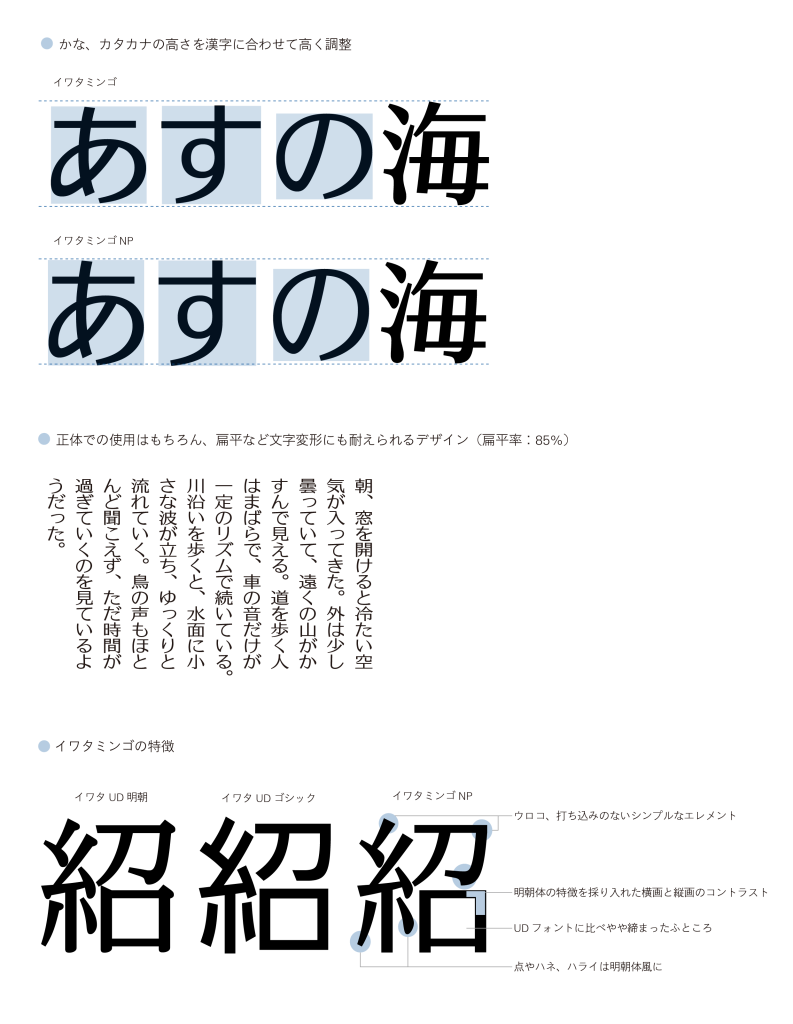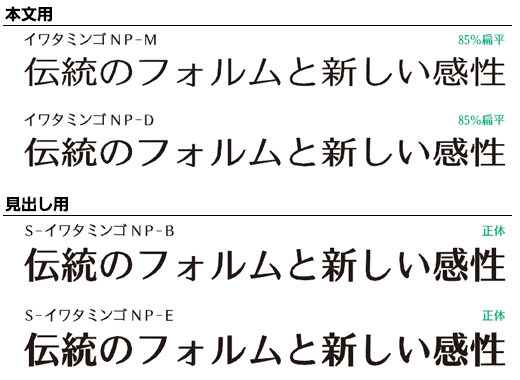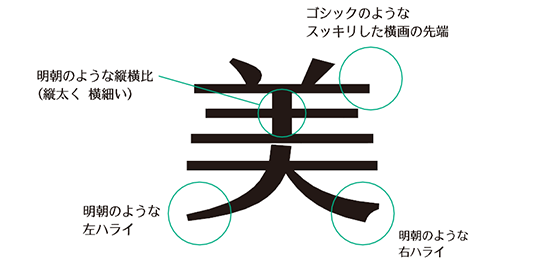
すっきりして優しい表情を持つ「イワタミンゴ」を新聞本文用にリニューアルしました。新聞全体への使用はもちろん、ラジオ・テレビ番組欄や生活面などへの部分的な使用も、彩りや変化のある紙面づくりに効果的です。文字セットは共同通信社が策定した「U-PRESS」に独自に調査した拡張文字848 文字を加えた「イワタU-PRESS」に対応しています。
書体デザインのポイント
明朝体のシャープさと可読性の高さ、ゴシック体のスマートな整列感を併せ持つ書体です。スッキリとした優しい表情を持つ、落ち着いたデザインです。